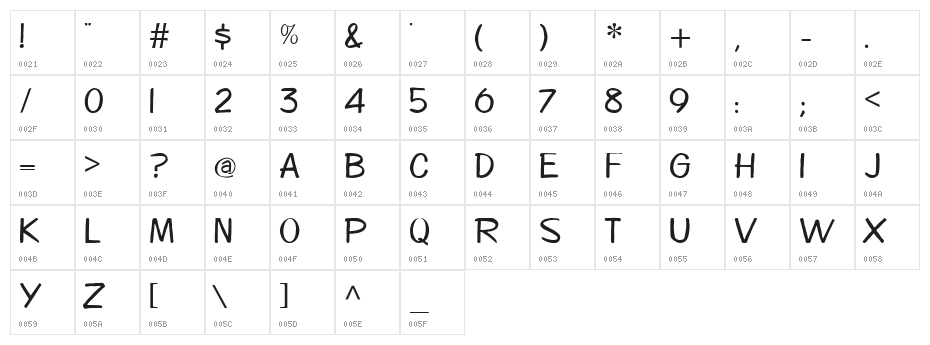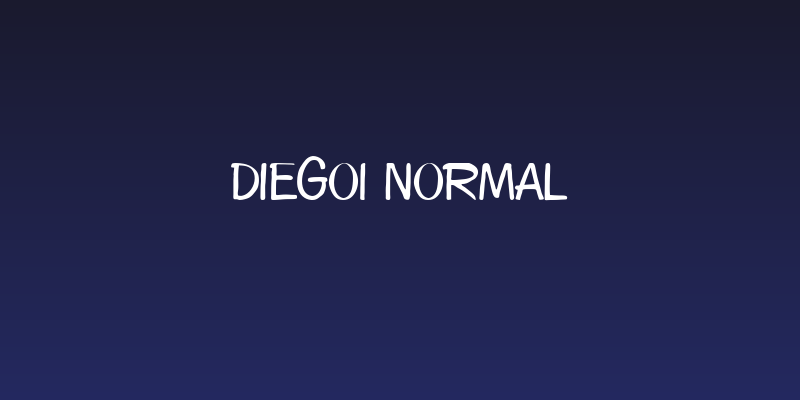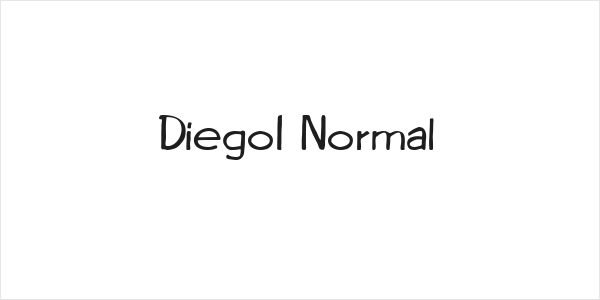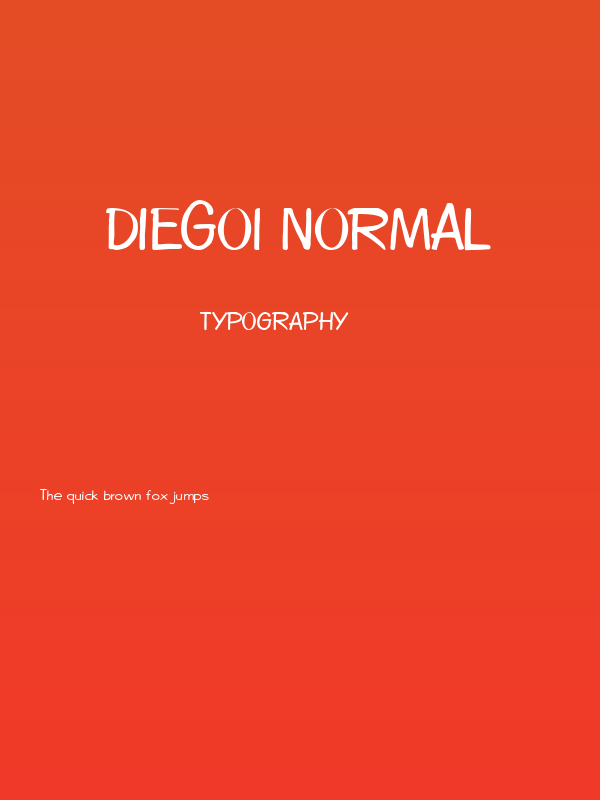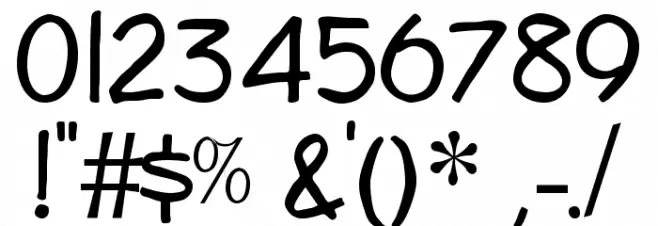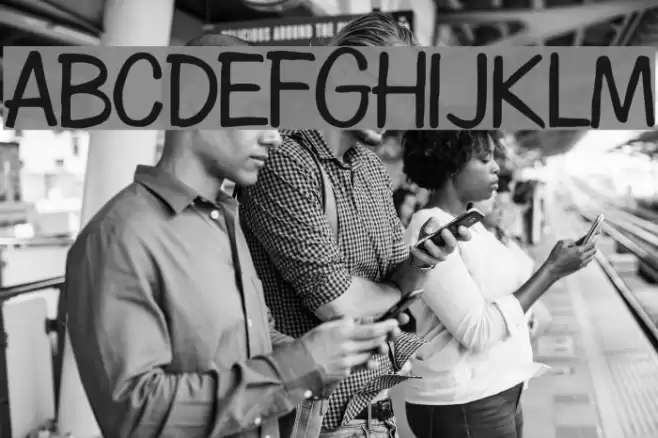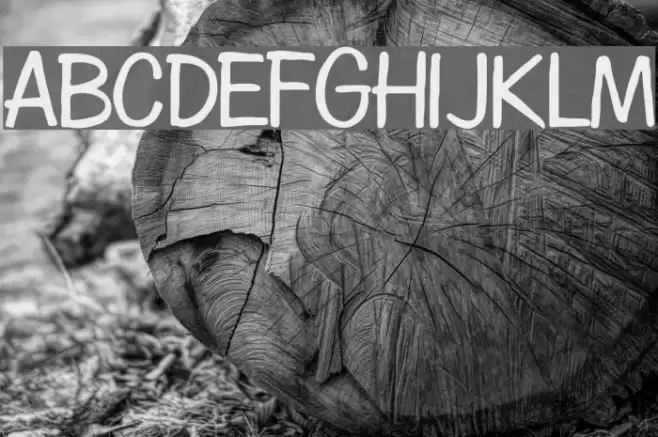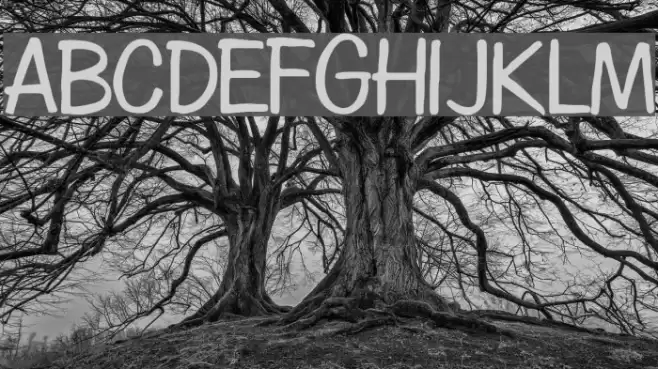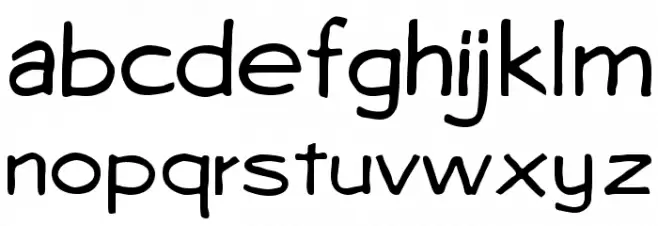
Diego1 Normal Font
| Общий стиль | Casual, Playful |
| Область применения | Headlines, Informal text, Branding |
| Рекомендуемые проекты | Ideal for children's books, greeting cards, informal branding, and playful social media graphics. |